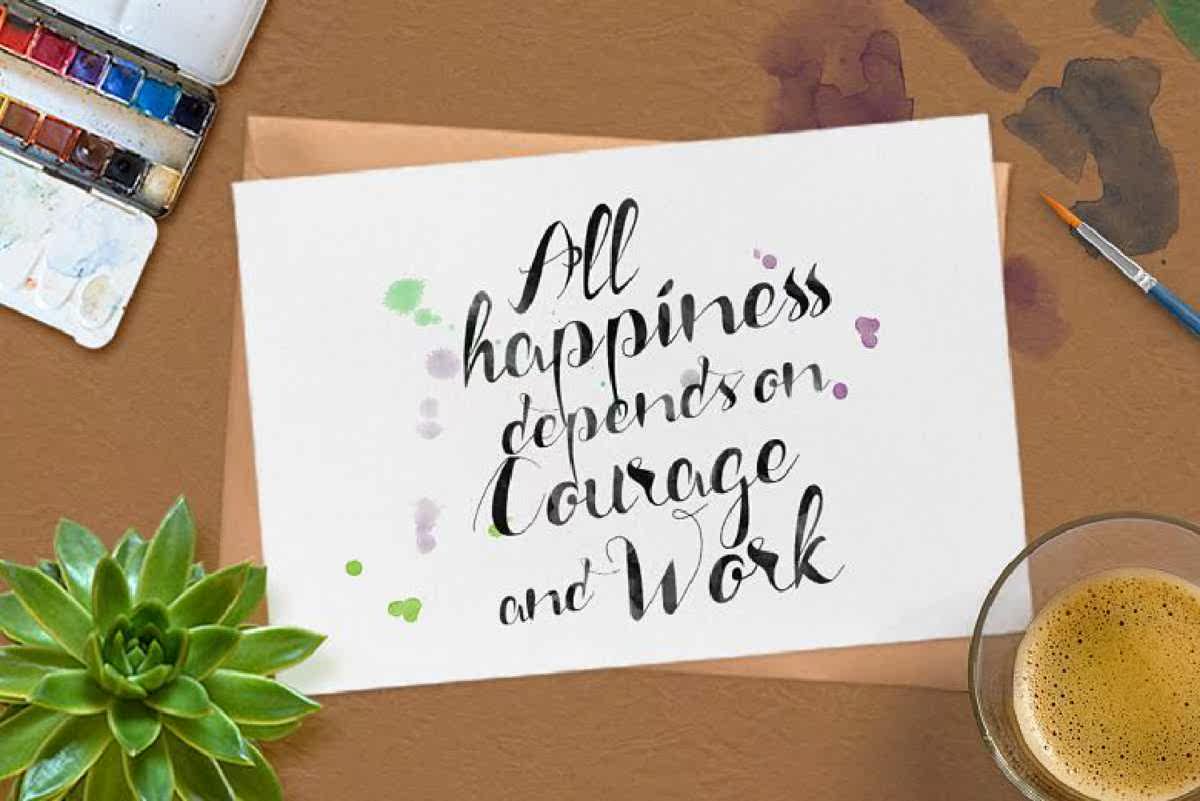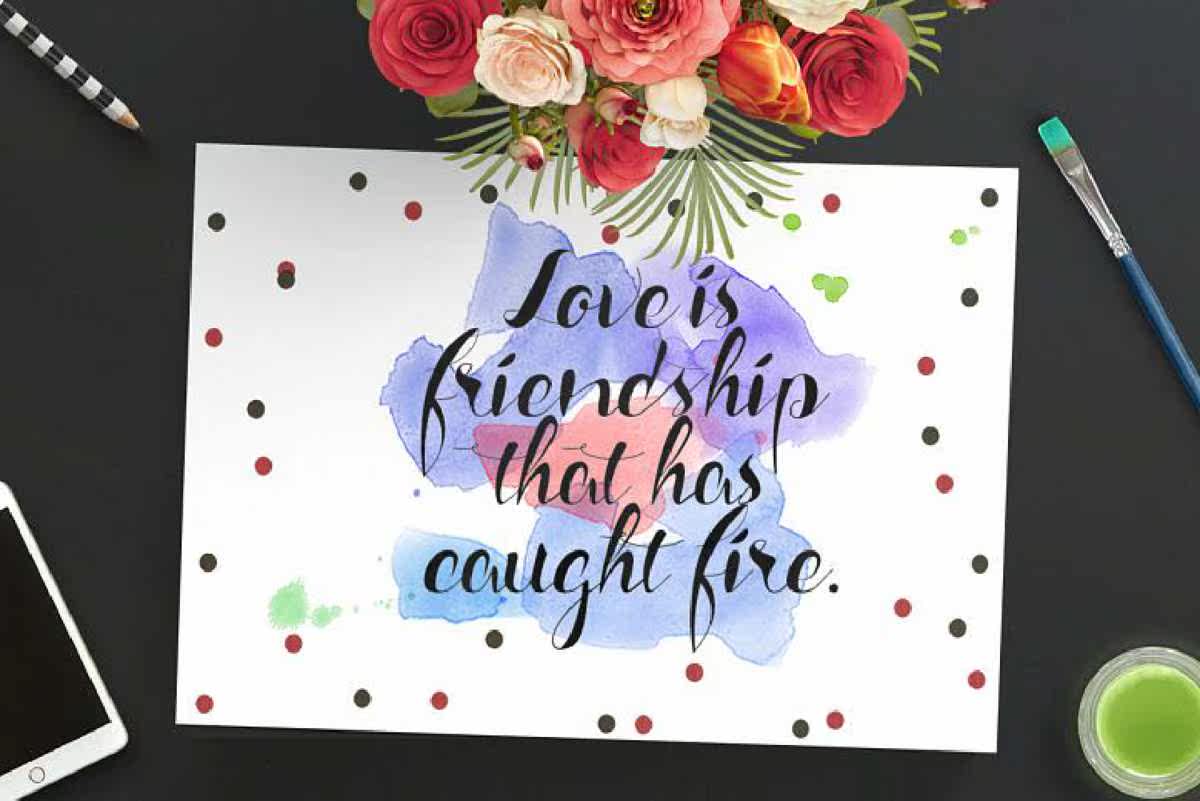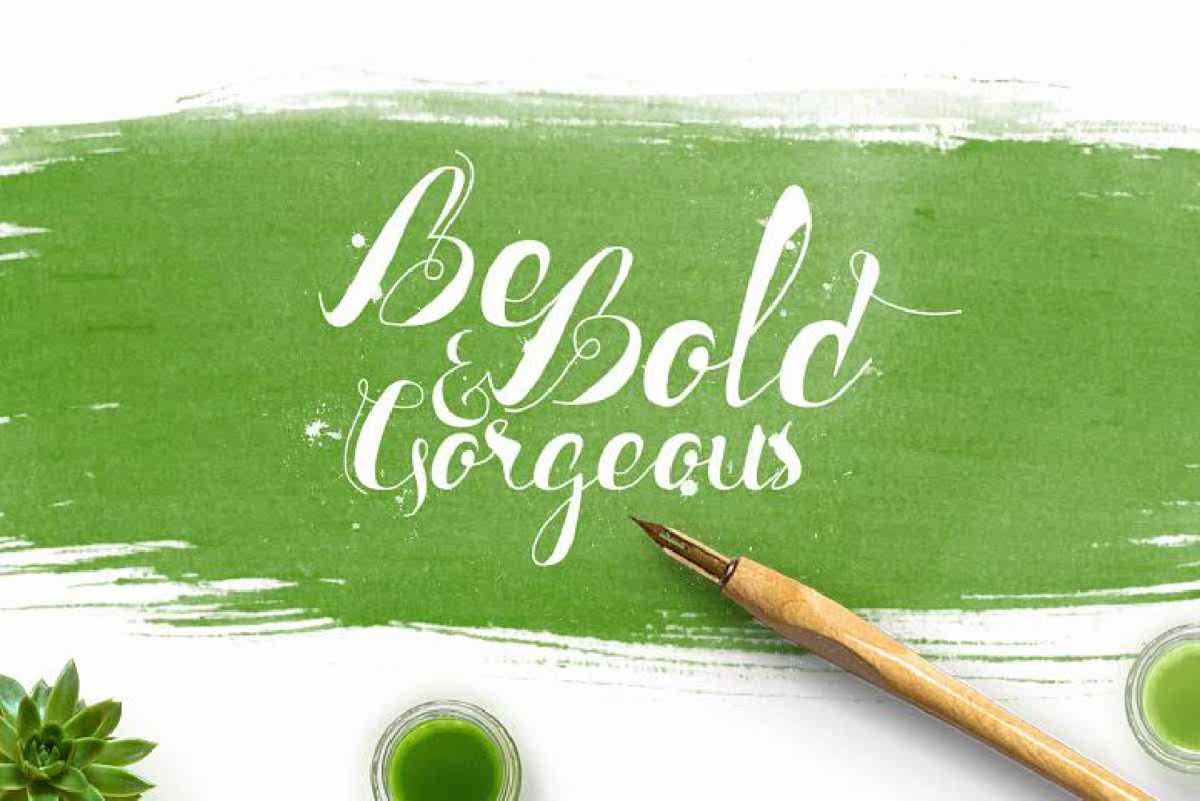
简介名为“NafeezaTypeface”的Gamodernscript此字体可用于信头、签名、徽标、婚礼宣传、海报、标题、标牌、标签、新闻、海报、t恤、徽章等。简介名为“NafeezaTypeface”的Gamodernscript此字体可用于信头、签名、徽标、婚礼宣传、海报、标题、标牌、标签、新闻、海报、t恤、,国家经贸委。